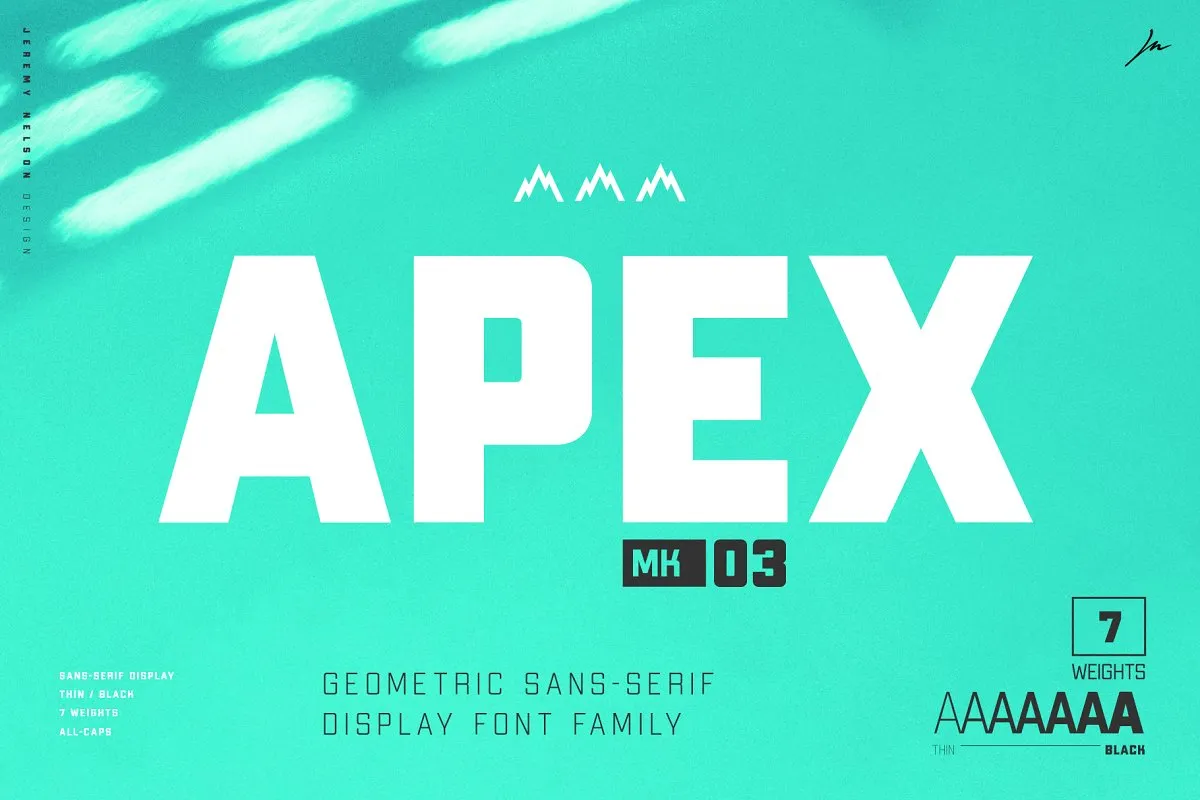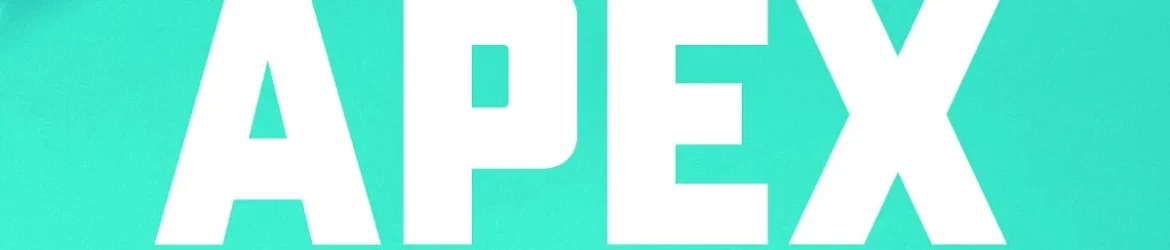
Apex Mk3 Font Family – Download Grátis
Bem-vindo ao download da Apex Mk3 Font Family. Esta é uma tipografia sans-serif que se destaca no estilo gráfico. Sans-serif e condensada, esta tipografia humaniza tudo enquanto busca seu lugar em seus projetos mais emocionantes. A Apex Mark 3 é um tipo de exibição robusto inspirado nas formas geométricas clássicas, sans serif e tipos de blocos esforçados que funcionam como cavalos de trabalho. A simplicidade da forma dá a ela flexibilidade para uma ampla gama de usos enquanto seu quadro geométrico fornece a base para sua tonalidade decisiva. Descubra como Apex Mk3 pode revitalizar e enriquecer seus projetos visuais.